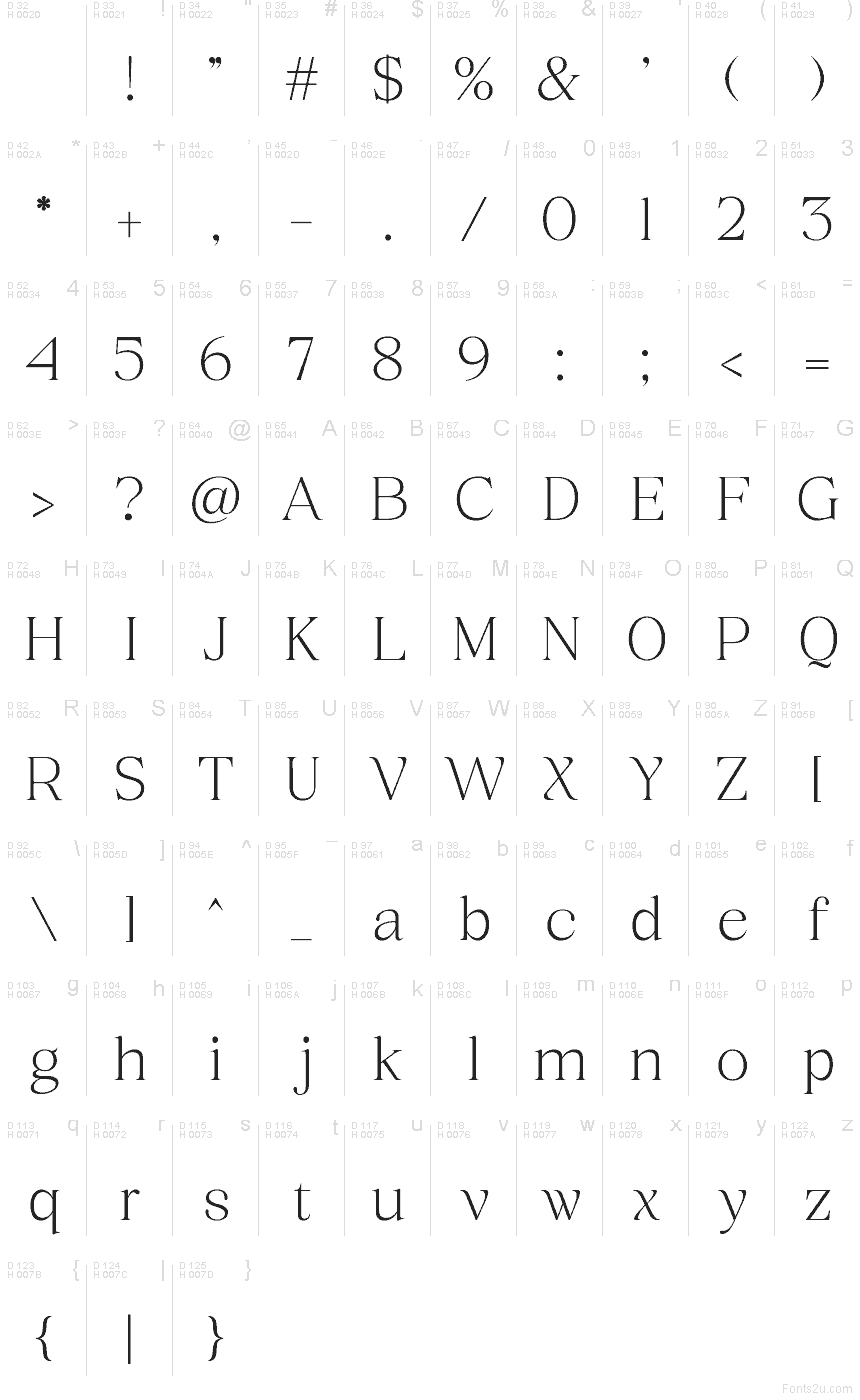
Scaver Thin di Glyphminds Studios è un carattere serif gratuito ad alto contrasto con un'estetica cool e orientata al mondo della moda. Le lettere accostano curve sottili a grazie affilate e affusolate, conferendo al font un aspetto etereo e raffinato anziché severo, con un'eleganza editoriale che gli impedisce di apparire puramente classico.
È ideale per il branding di boutique, packaging di prodotti di bellezza, testate di riviste, inviti, o menu di gallerie d'arte e caffè in cui è importante mantenere un tono leggero e curato. Essendo un font gratuito, è perfetto per titoli brevi, copertine e loghi, poiché i suoi tratti lunghi e aggraziati e le giunture sottili donano anche a poche lettere una presenza composta ed elegante.